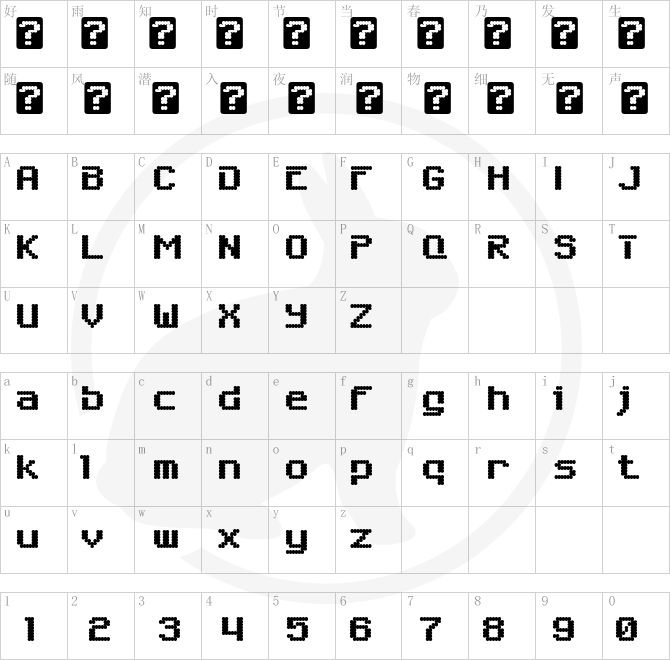
Six Eight Zero Nine Chargen.ttf字体下载,这款字体结构工整、笔画清晰,兼顾美观与易读性,适用于标题、正文、海报、包装、LOGO 等多种场景。字形优雅稳定,风格百搭耐看,适配日常排版与创意设计,让文字呈现更舒适、更具质感。Six Eight Zero Nine Chargen.ttf字体下载一笔一画,皆是细节,以均衡的比例、流畅的线条打造舒适视觉体验,字形端正大气,风格简约现代。无论是商业设计、品牌宣传还是日常排版,都能轻松驾驭,让文字更有格调与力量。Six Eight Zero Nine Chargen.ttf字体下载字体下载。